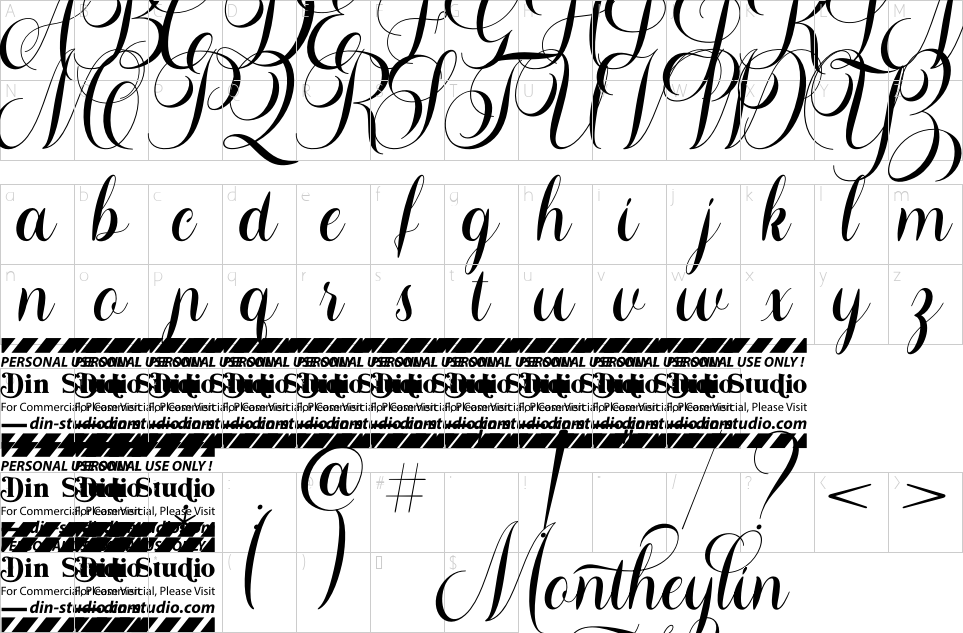
Montheylin Font | 1001 Free Fonts – Fonte Grátis
Descubra a beleza natural e sofisticada da fonte Montheylin, uma fonte gratuita disponível para baixar tanto no Windows quanto no Mac. Desenvolvida pelo Din Studio, esta fonte gráfica apresenta um conjunto impressionante de caracteres, com um equilíbrio perfeito entre simplicidade e elegância. Ela é perfeita para criar design gráfico atraente e bem-sucedido, seja em aplicativos de design de gráficos ou em projetos de escritório. Com seu design cuidadosamente pensado e sua vasta gama de caracteres, a Montheylin Font pode ser usada em qualquer tipo de aplicação digital. Seja para criar um logotipo, um site personalizado, ou até mesmo um diagrama de fluxo, esta fonte oferece o estilo e a versatilidade necessários para tornar seu projeto único e atraente. Com mais de 3.377 downloads, é evidente que muitos designers encontram a Montheylin font valiosa e poderosa. Descubra por si mesmo o poder desta fonte única.